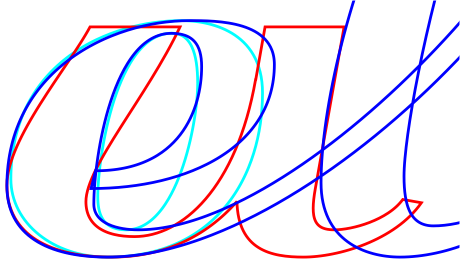
Los trazos de la tipografía
Para terminar el último día del año 2012 quiero dedicar este post para mostrar las letras —algunas— del nombre del nuevo logotipo de Vuelo 213. En la imagen aparecen la superposición de las letras «u» (rojo), «e» (azul) y «o» (cian). Lo que quiero señalar son las semejanzas y diferencias entre cada una de estas tres letras. Por lo pronto habrá que esperar un tiempo para conocer más detalles del nuevo logo de este blog.